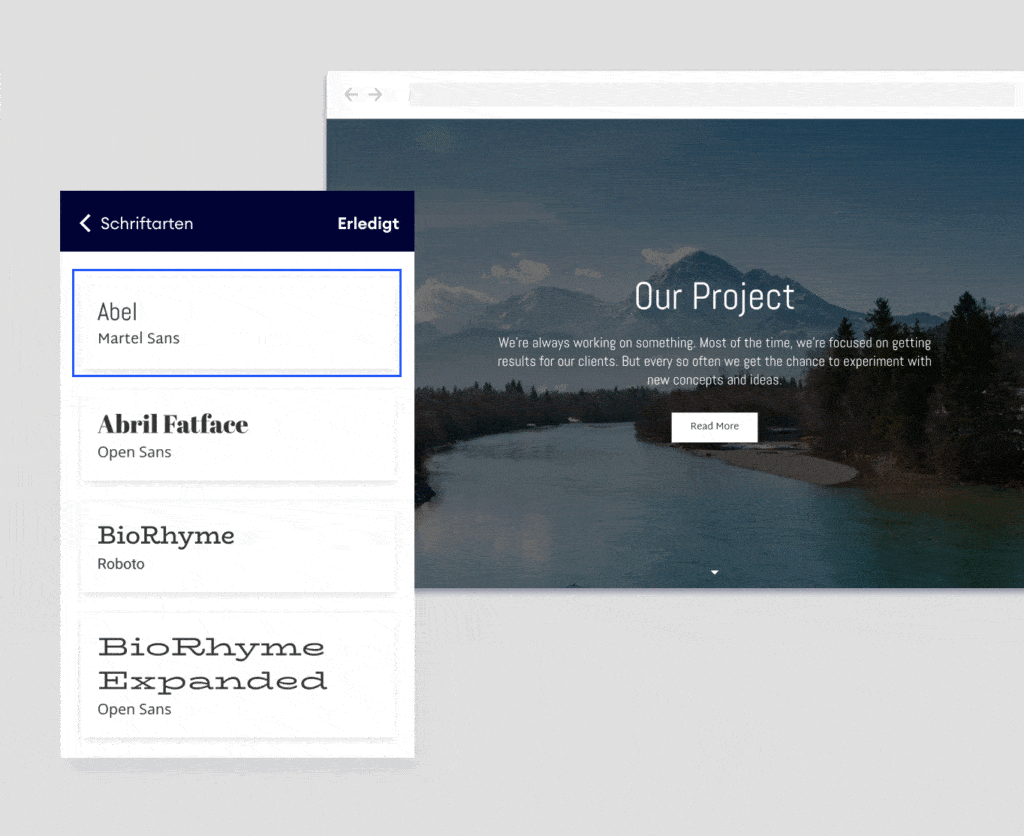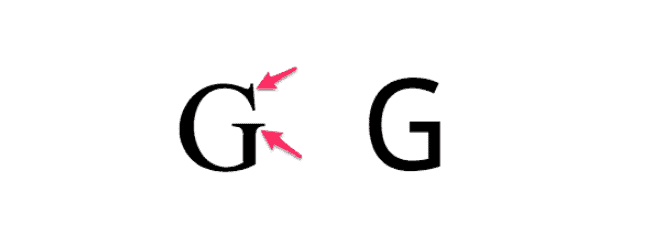
Bei einer individuellen Website denken die meisten zunächst an tolle Bilder, inspirierende Texte und eine Farbauswahl, die perfekt zu eurem Markendesign passt. Schriftarten kommen den wenigsten in den Sinn. Doch dabei gehört die richtige Schrift genauso zur Markenpersönlichkeit dazu, wie die eben genannten Elemente.
Um euch die Suche nach der passenden Jimdo Schriftart zu erleichtern, haben wir für euch ein umfangreiches Paket aus Schrift-Kombinationen geschnürt. Wie ihr daraus die ideale Auswahl für eure Website findet und warum Schriftarten generell ein wichtiges Thema sind, erfahrt ihr in diesem Artikel.
Schrift macht Eindruck
Welche Schriftart ihr für eure Texte auswählt, sollte eine ganz bewusste Entscheidung sein. Denn genau wie eure Bildauswahl und eure Farbpalette bestimmt eure Schrift den ersten Eindruck, den eure Besucher*innen von eurer Website bekommen.
Wir empfehlen daher, bei der Auswahl eurer Schriftarten vor allem auf drei Dinge zu achten:
- Leserlichkeit. Dass Besucher*innen eure Texte überhaupt lesen können, ist das Allerwichtigste. Um schicke Design-Schriften, die nur mit großer Anstrengung zu entziffern sind, solltet ihr daher einen großen Bogen machen. Entscheidet euch stattdessen für Schriftarten, die auf allen Bildschirmgrößen gut zu erkennen sind.
- Stil. Jeder hat seinen persönlichen Stil – auch euer Business. Fragt euch daher: Ist eure Marke mehr der verspielt-kreative Typ oder kommt sie eher bodenständig daher? Abhängig davon solltet ihr Schriftarten auswählen, die diese Markenpersönlichkeit optimal vermitteln.
- Lauflänge. Die Breite einzelner Buchstaben variiert von Schriftart zu Schriftart. Das führt dazu, dass Texte in verschiedenen Schriften unterschiedlich lang aussehen. Das kann besonders bei Überschriften einen großen Unterschied machen. Sucht euch deshalb eine Schriftart aus, die nicht zu viel Platz in Anspruch nimmt. Ebenso sollte sie nicht zu gedrungen wirken. Zielt stattdessen auf die goldene Mitte.
Welche Typen von Schriftarten gibt es?
Es gibt viele Möglichkeiten, Schriftarten zu kategorisieren. Damit es nicht zu kompliziert wird, wollen wir uns auf eine grobe Einteilung in drei verschiedene Typen beschränken: Serifen-, serifenlose und dekorative Schriftarten.
Serifen-Schriften
Die Wurzeln der Serifen reichen bis in die griechisch-römische Antike zurück, als Wörter noch in Stein gemeißelt wurden. Da das aber nicht so einfach war, entstanden beim Meißeln kleine Ausläufer an den Endpunkten der Buchstaben – so zumindest eine der gängigsten Theorien.
Diese Ausläufer wurden im Laufe der Zeit zu festen Bestandteilen der Buchstaben, selbst als Hammer und Meißel beim Schreiben keine Rolle mehr spielten. Heutzutage findet ihr Serifen-Schriften häufig in Büchern, Zeitschriften, Zeitungen und anderen Druckerzeugnissen. Der Grund: Serifen sollen das Lesen von gedruckten Zeilen erleichtern.
Zu den bekanntesten Serifen-Schriften gehören zum Beispiel Times New Roman, Garamond oder Baskerville.
Serifenlose Schriftarten
Als die ersten Computerbildschirme aufkamen, zeigte sich schnell, dass Serifen aufgrund der niedrigen Auflösung quasi nicht erkenn- und anzeigbar waren. Also entwickeln Designer mehrere Schriften, die trotz niedriger Pixelanzahl klar und deutlich angezeigt wurden. Dabei verzichteten sie komplett auf Serifen und andere Zierelemente.
Einige der gebräuchlichsten serifenlosen Schriften sind beispielsweise Arial, Lato oder Verdana.
Dekorative Schriftarten
In dieser breit gefächerten Kategorie fassen wir Zierschriften, Schreibschriften und andere Design-Schriftarten zusammen. Diese Schriftarten bieten jede Menge Persönlichkeit und Abwechslung, oft bleibt dabei aber die Leserlichkeit auf der Strecke.
Deswegen eignen sich dekorative Schriftarten eher für kurze Texte oder Wortgruppen – etwa Überschriften oder euer Firmenlogo. Für längere Absätze sind Schriftarten aus den anderen beiden Kategorien eindeutig die bessere Wahl.
Die Psychologie der Schriftarten
Genau wie Farben lösen auch Schriften bestimmte Gefühle und Reaktionen aus. Denn auch wenn es sich “nur” um Buchstaben handeln mag, verbinden wir doch unterbewusst zahlreiche Eindrücke und Erfahrungen damit.
Passen Aussage und Schriftart nicht zusammen, fällt uns das sofort auf. Stellt euch einfach ein Bestattungsunternehmen vor, das mit Comic Sans wirbt. Sicher werdet ihr euch zweimal überlegen, diesen Bestatter*innen die sterblichen Überreste von Tante Amalia anzuvertrauen.
Oder wie wäre es mit einem Design-Büro, das sich auf Kinderbücher spezialisiert hat, aber eine Schrift wie Libre Baskerville verwendet?
Hier wäre eine verspielte Schriftart wie Londrina Sketch eindeutig die bessere Wahl.
Anders als bei Farben gibt es keine ausführlichen Anleitungen und große Studien darüber, welche Schrift was bei wem auslöst. Die “richtige” Schriftart zu finden, ist daher mehr Bauchgefühl als Wissenschaft. Wenn euer Gefühl bei einer Schrift also sagt “nein, lieber nicht”, dann hört darauf und versucht es mit einer anderen.
Die Entscheidung, welche Schriftarten ihr für eure Website verwendet, solltet ihr nicht leichtfertig übers Knie brechen. Denn die richtige Schrift gehört genauso zur visuellen Identität eures Business, wie euer Logo-Design und eure Unternehmensfarben.
Nehmt euch also ein wenig Zeit und klickt euch durch unsere Jimdo Schriftarten, bis ihr die Kombination gefunden habt, die auch wirklich zu euch passt. Denn mit einer guten Schrift hinterlasst ihr auch einen guten Eindruck.